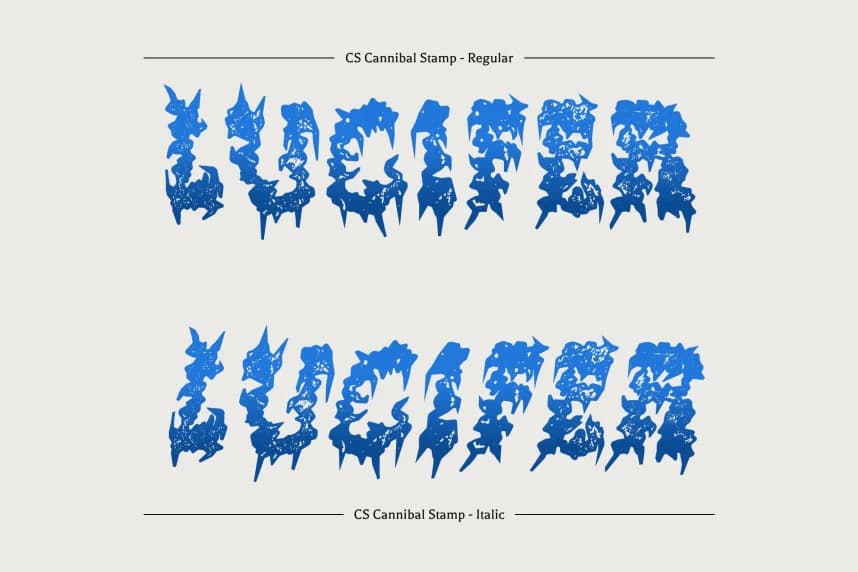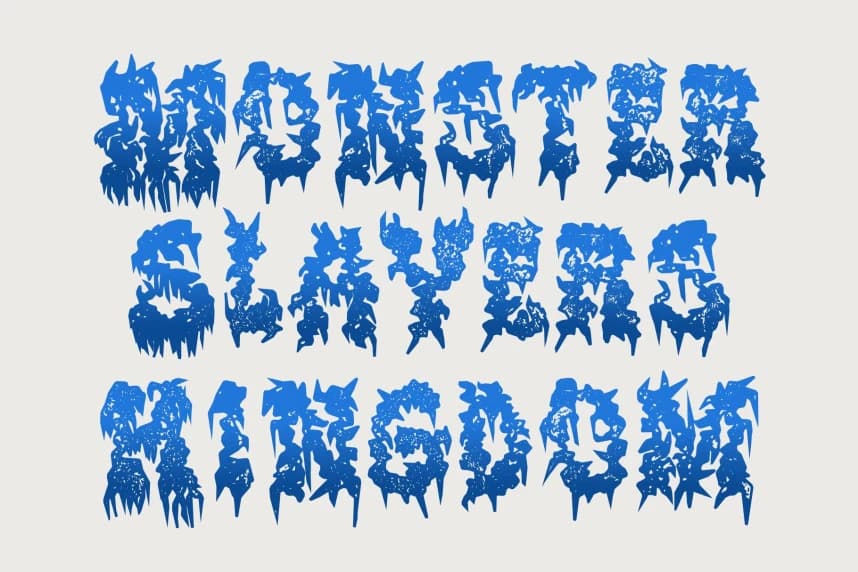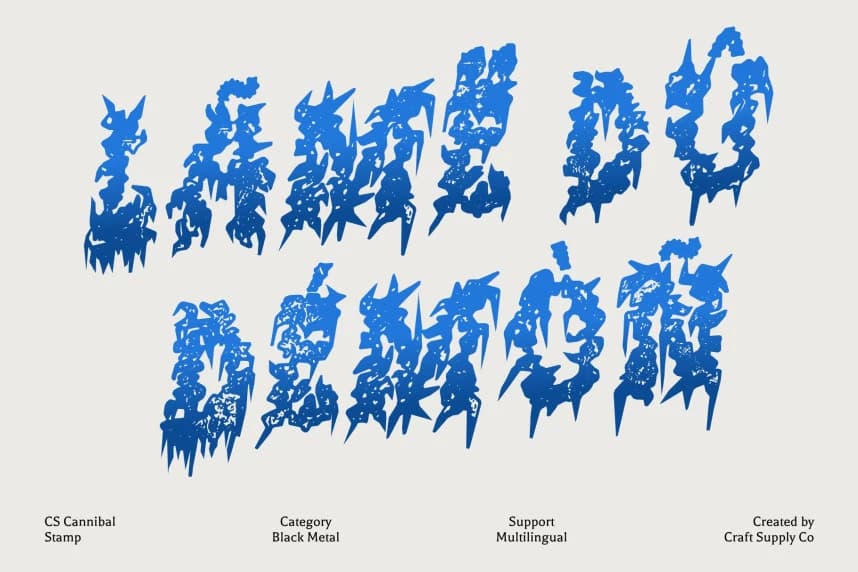
CS Cannibal Stamp Yazı Tipi
CS Cannibal Stamp Font – Black Metal Chaos with Vintage Brutality – Brutal Black Metal Display Font with Raw Texture. Bu, ekstrem metal estetiğinin ham yoğunluğunu ve karanlık mistisizmini yakalamak için tasarlanmış bir Black Metal Display Font'tur.
CS Cannibal Stamp Font – Vintage Brutality ile siyah metal kaosu, Brutal siyah metal gösterim fontu ile ham doku. Bu, ekstrem metal estetiğinin ham yoğunluğunu ve karanlık mistisizmini yakalamak için tasarlanmış bir siyah metal gösterim fontudur.